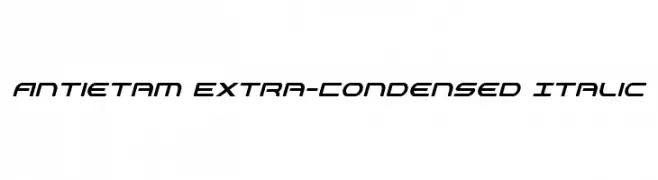
A sleek, italicized, extra-condensed font with a modern and streamlined appearance.
近期热门包括 Antietam Extra-Condensed Italic, Antietam Expanded, Antietam Expanded Italic, Antietam Italic and Antietam 3D Italic 它们在清晰度与个性之间取得平衡,适用于科技品牌、编辑排版与社媒视觉。